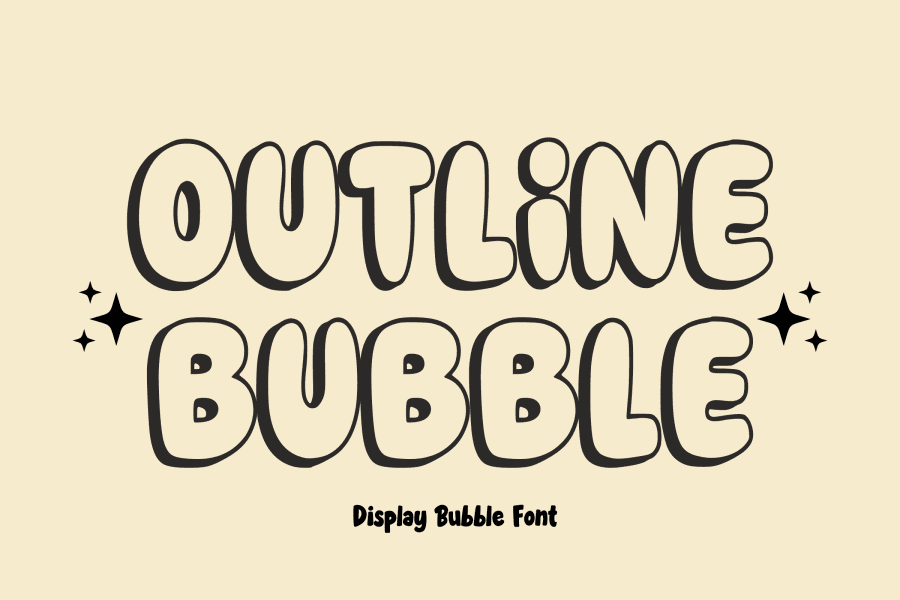
Bubble Font Việt hóa là nhóm phông chữ thuộc dòng Display mang phong cách bong bóng phúng phính, tròn xoe và tràn đầy năng lượng vui tươi của nghệ thuật Pop-art và Graffiti thập niên 1990. Với cấu trúc nét chữ căng mọng như những quả bóng bay vừa được bơm hơi, nhóm phông chữ này là lựa chọn số một cho các thiết kế bao bì bánh kẹo, nhãn dán ly trà sữa, đồ ăn vặt và sản phẩm đồ chơi trẻ em. Doozypack.vn cung cấp link tải Bubble Font Việt hóa chuẩn kỹ thuật, giúp bạn sở hữu trọn bộ phông chữ bong bóng đáng yêu mà không lo gặp bất kỳ lỗi hiển thị dấu thanh nào khi thiết kế in ấn.
Đặc điểm thẩm mỹ độc đáo của các dòng Bubble Font
Bubble Font không đi theo quy chuẩn nghiêm nghị của các phông chữ hình học; nó mở ra một không gian thị giác ngập tràn sự ngọt ngào, tạo cảm giác thân thiện và kích thích sự hào hứng cho người xem.
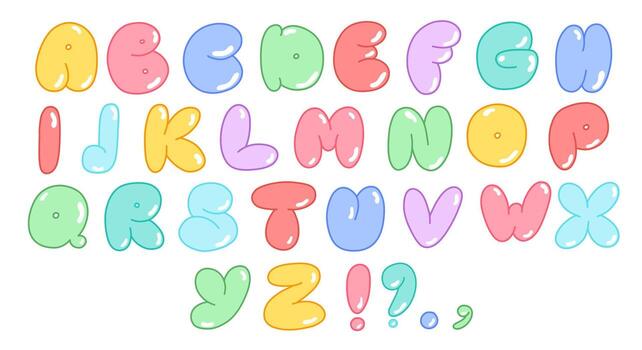
Hình khối bong bóng phúng phính và tràn đầy năng lượng tích cực
Đặc trưng lớn nhất của Bubble Font Việt hóa là các đường nét mập mạp, uốn lượn phồng căng như những viên kẹo ngọt hoặc bong bóng xà phòng rực rỡ. Cấu trúc chữ có độ dày nét (weight) cực lớn cùng những mảng mực đặc đầy đặn, tạo ra một sức hút thị giác vượt trội. Khi đặt phông chữ này làm tiêu đề trên bao bì, tên sản phẩm của bạn sẽ ngay lập tức trở thành tâm điểm của sự chú ý, tạo cảm giác thân thiện và kích thích vị giác của khách hàng ngay từ cái nhìn đầu tiên.
Đường nét bo tròn tuyệt đối xóa bỏ sự khô cứng
Tất cả các điểm kết thúc và góc nối của dòng font chữ này đều được xử lý bo cong mượt mà, loại bỏ hoàn toàn cảm giác sắc nhọn cứng nhắc. Thiết kế này mang lại tâm lý an tâm, gần gũi và ấm áp, cực kỳ ăn ý với các thương hiệu dành cho mẹ và bé, đồ chơi sáng tạo hoặc các dòng sản phẩm đồ ăn vặt hướng tới học sinh, sinh viên.
Ưu điểm nổi bật của bộ Bubble Font Việt hóa
Khi ứng dụng các phông chữ nét béo mập vào thị trường trong nước, sự chỉn chu về dấu câu là yếu tố quyết định đến tính thẩm mỹ của ấn phẩm:
- Khắc phục triệt để lỗi dấu tiếng Việt: Phiên bản Việt hóa đã được đội ngũ thiết kế trau chuốt thủ công từng dấu câu. Các dấu sắc, huyền, hỏi, ngã, nặng được vẽ căng mọng, bo tròn đồng điệu với thân chữ gốc, không gây cảm giác chắp vá hay làm biến dạng cấu trúc chữ.
- Bảo đảm tính đồng nhất thương hiệu: Việc tải font Việt hóa Bubble chuẩn giúp bạn tự tin dàn trang tiêu đề tiếng Việt mà không lo hiện tượng lỗi ô vuông hay nhảy về font hệ thống khô khan.